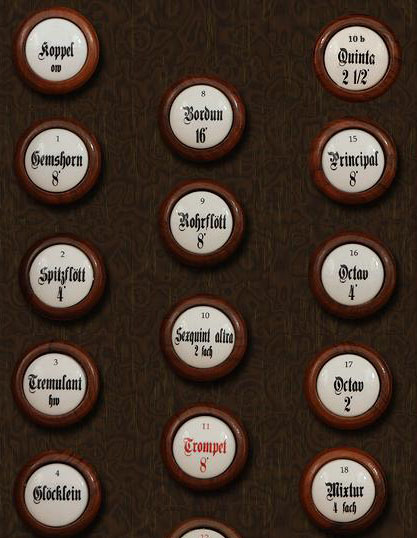
Ja, wir wissen alle, dass typoböse ist, wer ein »Fuß-Zeichen« statt eines Apostrophs setzt. Aber wie sieht ein »Fuß-Zeichen« in einer gebrochenen Schrift aus; quasi ein gebrochener Fuß? Da bin ich mir sehr unsicher, weil die letzte Fraktur mit der ich zu tun hatte, die meines Schlüsselbeins war.
Es geht um die Beschriftung von Orgelregistern nach historischem Vorbild (Denkmalorgel von 1860). Die Schrift ist die Walbaum Fraktur. Orgelregister werden in Fuß angegeben. Die Angabe bezieht sich auf die Fuß-Länge der Pfeifen.
Ganz spontan: so wie es gut aussieht. Bei der Disposition einer Orgel gibt es keinerlei Möglichkeiten der Verwechselung; theoretisch könnte man die Fuß-Auszeichnung auch weglassen und die Organisten würden trotzdem noch genau wissen was gemeint ist. Ich habe mal auf die Schnelle einige Photos im Netz durchgesehen und Versionen 1 scheint die wohl üblichste zu sein.
Eigentlich müsste das Fußzeichen dieses sein: ′ (U+2032, Prime), nur habe ich auf die Schnelle keine Walbaum-Fraktur gefunden, die dieses Zeichen beinhaltet, ich würde die 3. und 4. Variante nicht nehmen, zu den anderen kann ich jetzt gerade auch nichts sagen.
Keines der Beispiele ist richtig. Das vorletzte paßt, wenn Du den Strich etwas im Uhrzeigersinn kippst.
Das Fußzeichen und andere mathematsiche Zeichen gab es in Frakturschriften nicht; man hatte damals normalerweise einen eigenen Satz Formelzeichen, den man dann zu allen Textschriften benutzte.
Ist überhaupt ein Zeichen für Fuß definiert? Oder wird streng genommen nur das Zeichen für die Bogenminute auch für Fuß verwendet, weil kein eigenes existiert?
Laut Forssmann und de Jong ist es das gleiche Zeichen, wie die Bogenminute. Jetzt bleibt nur die Frage: wie sieht eine Bogenminute in der Walbaum Fraktur aus?
Eine Alternative wäre noch das Ausschreiben des Wortes »Fuß«. Das geht aber leider nicht immer.
Laut Forssmann und de Jong ist es das gleiche Zeichen, wie die Bogenminute. …
Ja, das war schon klar, meine Frage war ob Fuß als Zeichen so definiert ist oder ob einfach das Minutenzeichen dafür hergenommen wird. Als Einheitenzeichen habe ich bisher nur "ft" gefunden. Forssmann und de Jong sind schließlich Typographen und kein Normierer. ;-)
Noch mal anders herum: warum willst Du auf Teufel komm raus das »richtige« Zeichen verwenden? Gerade wenn es um eine historische Orgel geht wäre es doch eigentlich viel sinnvoller, sich darauf zu verlegen was 1860 üblicherweise für die Bezeichnung verwendet wurde?
Nur mal ein willkürliches Beispiel:
Das Bild zeigt eigentlich ganz schön die Priorität: die Klangfarbe ist zunächst wichtigstes Erkennungsmerkmal, die Oktave kommt danach und das Fußzeichen ist im Grunde vollkommen unerheblich.
Jetzt bleibt nur die Frage: wie sieht eine Bogenminute in der Walbaum Fraktur aus?
Wie ich schon geschrieben habe: In der Walbaum-Fraktur gab es mit an Sicherheit grenzender Wahrscheinlichkeit kein Fuß-/Minutenzeichen. Man hatte damals in Setzereien einen Satz mathematischer Zeichen, die man dann einfach zu jeder Textschrift benutzt hat.
Das Zeichen für Fuß/Minute ist ein nach rechts geneigter Strich, der sich nach unten verjüngt. Wenn Du das Zeichen in Deinem vorletzten Beispiel nach rechts kippst, hast Du ein einwandfreies Fußzeichen.
warum willst Du auf Teufel komm raus das »richtige« Zeichen verwenden?
Nennen wir es sportlichen Ehrgeiz
Das Bild zeigt eigentlich ganz schön die Priorität: die Klangfarbe ist zunächst wichtigstes Erkennungsmerkmal, die Oktave kommt danach und das Fußzeichen ist im Grunde vollkommen unerheblich.
Auch an anderen Stellen bin ich pingelig, wenn es darum geht, dass Einheiten und Größen richtig geschrieben werden. Da sind mir die Sehgewohnheiten der Organisten genausowenig Beispiel, wie die Unart, auch im schriftlichen, bei Temperaturen das Celsius nach dem Grad wegzulassen, obwohl jedem klar sein könnte, dass man beim Wetter nicht von Winkeln spricht.
Ach ja: »Auf Teufel komm raus« find’ ich witzig – bei einer Kirchenorgel. Leider spielt der Organist auch so.
Ich habe eben mit dem Orgelbauer gesprochen: Es ist jetzt doch genug Platz, »Fuß« auszuschreiben, so wie es auf den Originalen auch zu lesen war. Obwohl ich ja jetzt wüsste, wie es richtig zu machen wäre.
… wenn es darum geht, dass Einheiten und Größen richtig geschrieben werden. …
Gab es zu Frakturzeiten überhaupt ein richtiges Fuß-Zeichen?
Da sind mir die Sehgewohnheiten der Organisten genausowenig Beispiel, wie die Unart, auch im schriftlichen, bei Temperaturen das Celsius nach dem Grad wegzulassen, obwohl jedem klar sein könnte, dass man beim Wetter nicht von Winkeln spricht.
Das kann man schon am Satz erkennen: Winkelangaben werden ohne Leerzeichen gesetzt, wohingegen Temperaturangaben immer mit Leerzeichen setzt. Wenn dann z.B. das »C« fehlt, dann ist immer noch klar, daß es sich um eine Temperaturangabe handelt, auch wenn dann die Skala der Angabe natürlich nach wie vor nicht klar ist. :tuschel:
Wegfallen tut da im Grunde gar nix. °C oder °F sind einfach relative Angaben, relativ zum Gefrierpunkt von Wasser (0 °C) oder der Körpertempertur vom Pferd (100 °F). Die Angaben werden auch mitnichten aus dem Gebrauch verschwinden, weil man sich nämlich unter 273 K im Grunde nichts vorstellen kann. Die absolute Skala ist in den Wissenschaften notwendig, im täglichen Gebrauch aber einfach unpraktikabel. Das ist wie beim Druck: die SI-Einheit ist hier pascal, welches da 10e-5 bar entspricht. Wer kann sich darunter schon noch etwas vorstellen? In der Physik und physikalischen Chemie unentbehrlich, im täglichen Gebrauch aber viel zu abstrakt.